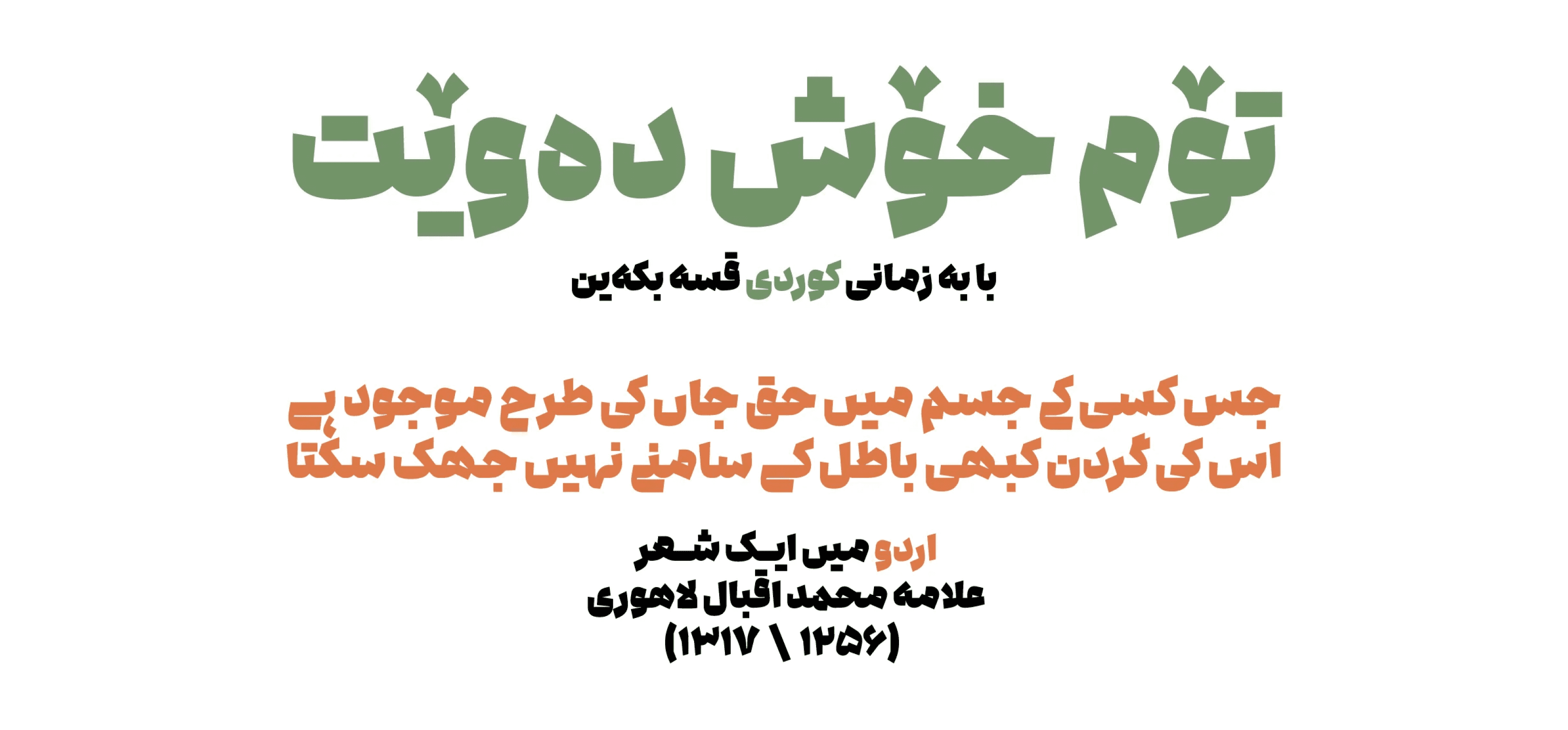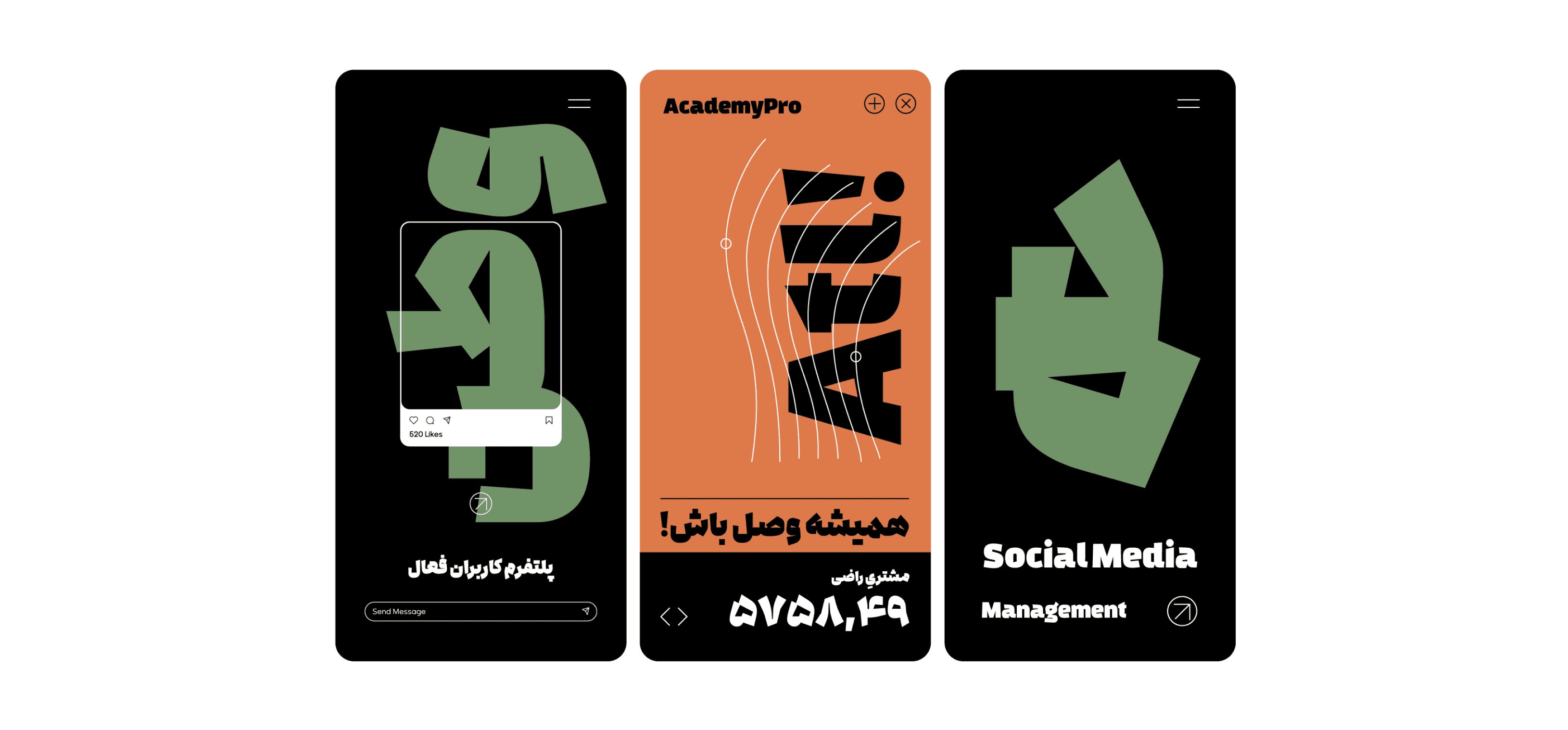
خط "ادامه" هو ثمرة جهودي في دراسة تفاصيل الهندسة في الخطاط الإيراني ضمن صف الأستاذ دامون خانجانزاده.
قمت بتحويل اسكتشاتي إلى أشكال قوية، وشيئًا فشيئًا طوّرت هذا الخط بهدف استخدامه في العناوين ذات الكلمة الواحدة والنصوص القصيرة، حتى اكتمل بشكل نهائي.